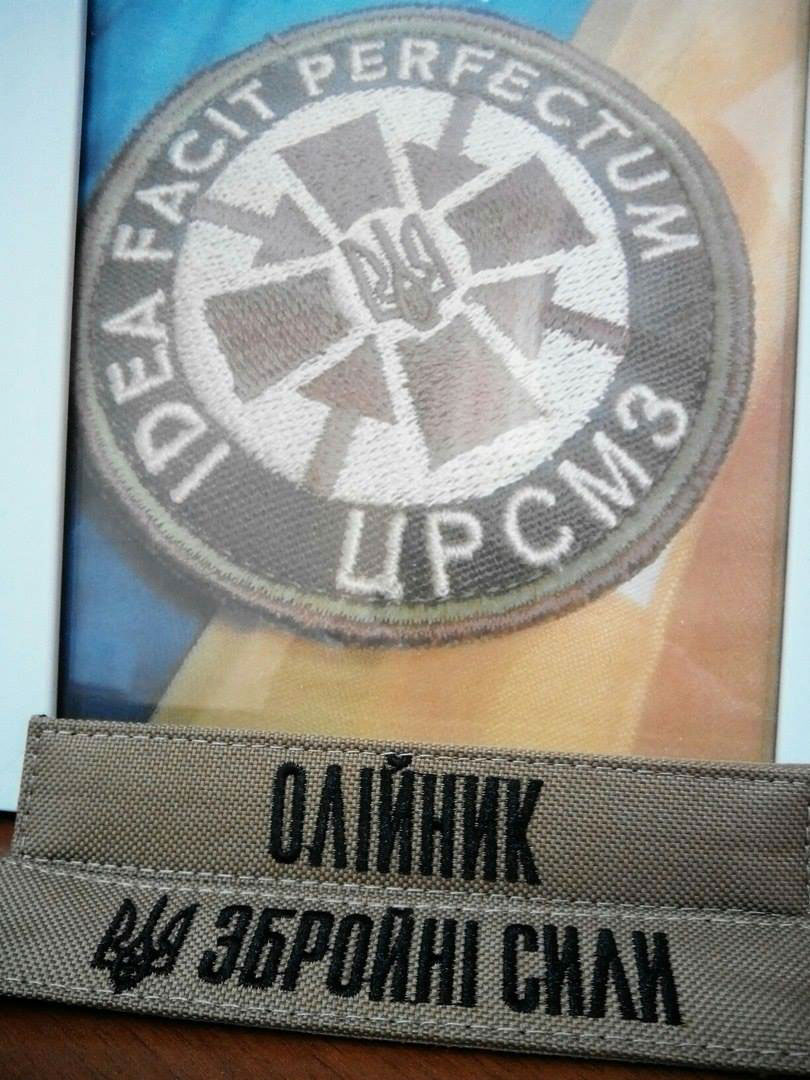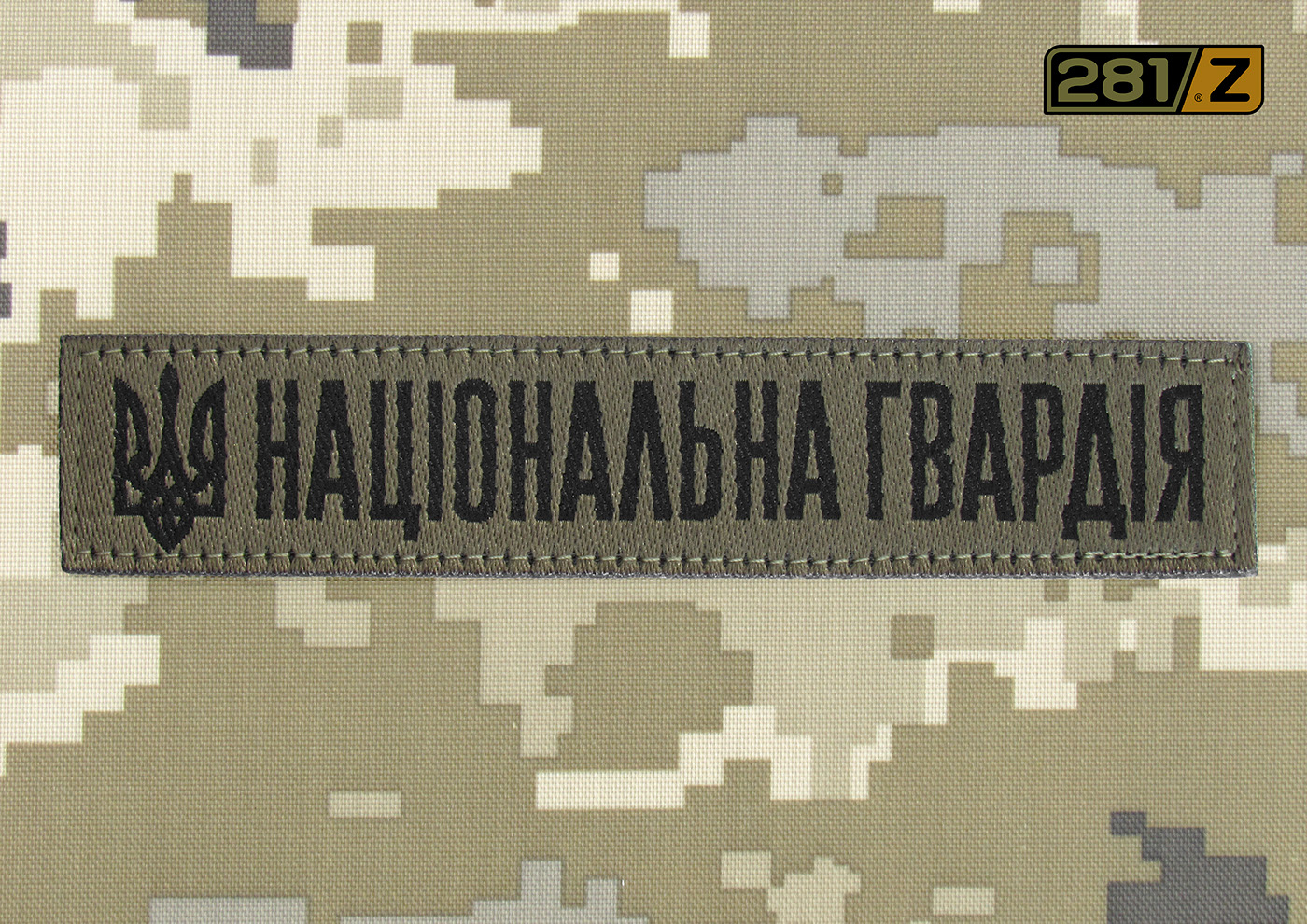
З початком військової агресії Російської Федерації проти України постала задача переоснащення української армії. У лютому 2015 року розпорядженням Міністра оборони було створено робочу групу з питань удосконалення матеріального забезпечення Збройних Сил України (директива 281/з). 12 січня 2016 року Олександр Полевара (один із розробників з ЦРСМЗ) запросив мене для розробки шрифта для нашивок (патчів) на волонтерських засадах для Збройних Сил України.
Нам був потрібен компактний шрифт, щоб текст читався не далі ніж два метри, набір знаків української абетки, а також підтримка мов наших союзників (США, Польща, Литва). Робоча назва шрифта UA ARMY. У планах розробка розвиненої сім'ї у декількох накресленнях. Всі права на шрифт передані мною Міністерству Оборони України.
Given the Russian aggression towards Ukraine, the task of re-equipping the army arose. In February 2015, Ukraine’s Minister of Defense set up a working group on improving procurement and supply of Ukraine’s Armed Forces (Directive 281/z). On the 12th of January 2016, Oleksandr Polevara (one of the developers at Center for Development and material support Ukraine's Armed Forces) invited me to design the fonts for the new patches of Ukraine’s Armed Forces pro bono. What we needed to create was a compact font based on Ukrainian character set with support of our allies’ languages (USA, Poland, and Lithuania) where the text could be legible from no further than two meters. The working title of the font is “UA ARMY”. There is a plan to develop an extended font family in several weights and styles. I have transferred all rights for the font to Ukraine’s Ministry of Defense.
Базовий шрифт / Base font UA ARMY Labels (light and bold versions)
Перші тести вишивки
First tests
Порівняння старих і нових нашивок (патчів)
Comparison of old and new patches
Текстова версія шрифта
Text version of typeface
Прикордонна служба на параді з нагоді 25-ї річниці Незалежності України з нашивками (патчами) нового зразка
The Border Guard on parade to mark the 25th anniversary of Independence of Ukraine with new model of patches